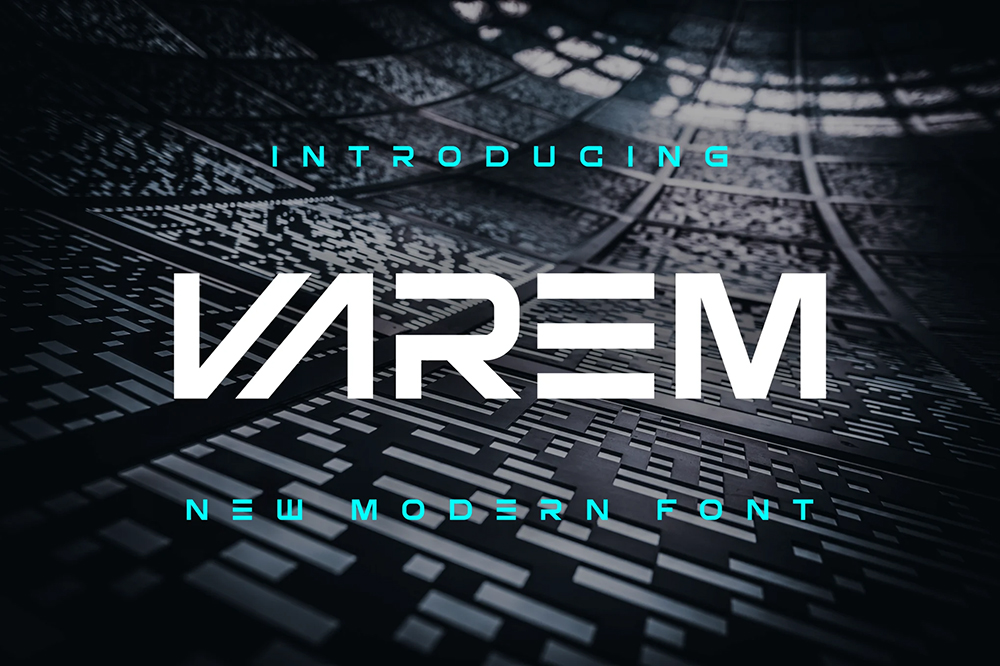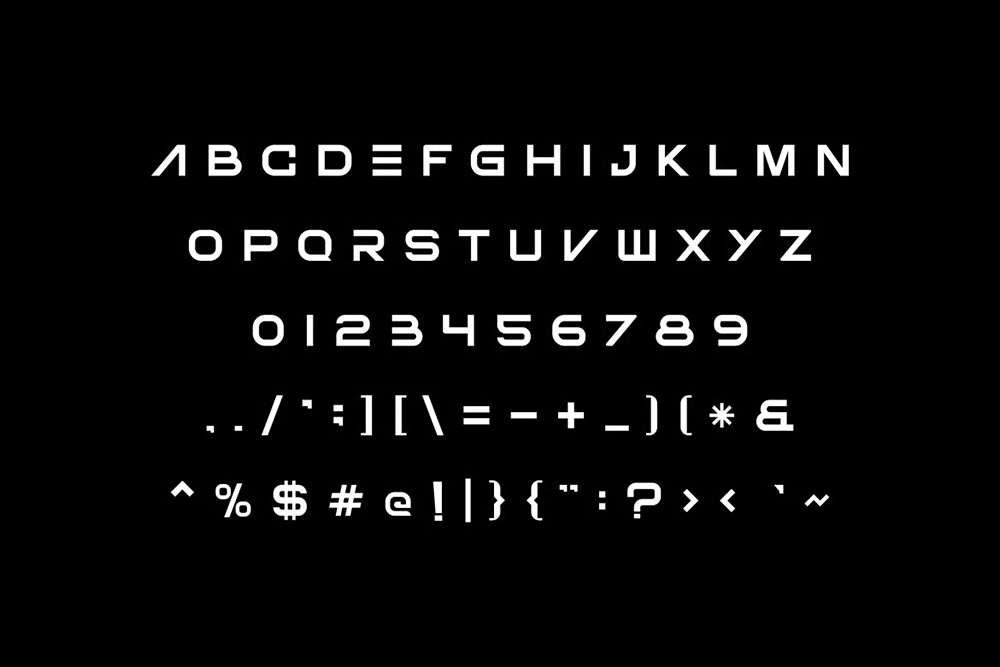
دانلود فونت انگلیسی Varem Font
فونت پرمیوم و انگلیسی Varem Font یک فونت نمایشی جسورانه و اصیل است. این فونت برای هر پروژه برندسازی مانند لوگو، چاپ تیشرت، ورزش و موارد دیگر مناسب است. در طیف گستردهای از کاربردها عالی است.
مزایای استفاده از فونت لاتین Varem چیست؟